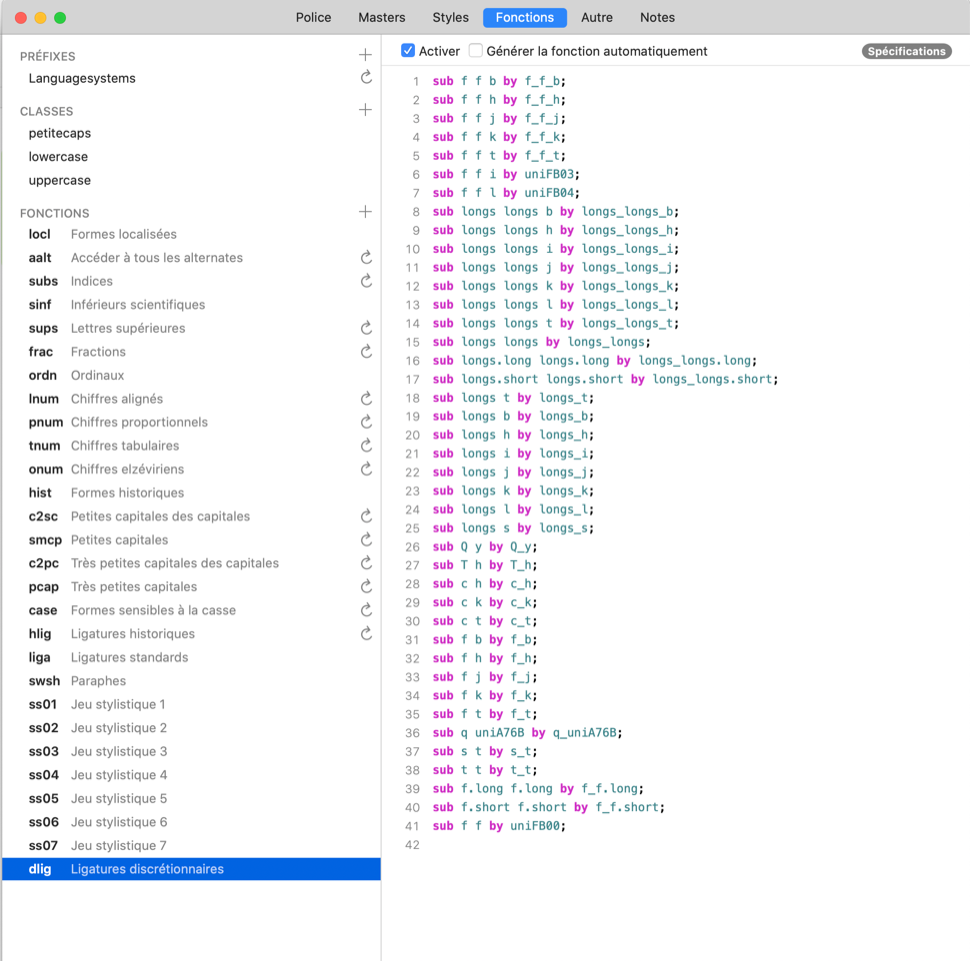
Message : Re: [typo] EB Garamond Variable. — Logiciel Glyphs (Mac OS) et ligatures
Subject:    Re: [typo] EB Garamond Variable. — Logiciel Glyphs (Mac OS) et ligatures
Je viens de télécharger le fichier .glyphs depuis le repo Github et ne vois aucun problème sur la fonte, qui est plutôt très bien développée. Pas de bugs sur le dessin des ligatures, des fonctions bien hiérarchisées, et toutes les espaces possibles.
Pourquoi avez-vous besoin de la fonte variable? Si c’est pour les ligatures, les OTF statiques suffisent amplement.
Pour activer ou pas les ligatures, l’EB Garamond dispose de différentes features OpenType pour activer ou non
— fi, fl, ffi, fil : LIGA (ligatures)
— ligatures s long : HLIG (ligatures historiques)
— fb, tt, ss, Qy… : DLIG (ligatures discrétionnaires)
Et sous HIST on peut activer les « formes historiques » comme le s long.
Le non-joiner est bien dans la fonte (U+200C), ainsi que toutes les espaces.
Plutôt que l’intégrer entre les glyphes, je vous recommande de n’activer que les features nécessaires. Ceci dit, la technique du non-joiner peut être utile pour faire des exceptions locales.
Dans l’urgence, si Octavio Pardo ne donne pas signe de vie ou que je ne
réussis pas à trouver un utilisateur de Glyphs disposé à me venir en
aide, j’ai trouvé un contournement qui suffira à régler le seul problème
majeur concernant l’usage des ligatures pour le client que j’évoquais :
introduire une espace de chasse nulle (WORD JOINER) entre certains
caractères pour bloquer les ligatures italiques « a/e/i/u-s »
indésirables au milieu d’un mot, empêchant de surcroît en italique les
ligatures attendues « st ») — un coup de chercher-remplacer avec
_expression_ rationnelle dans la copie, et le tour sera joué.
Évidemment, ça ne règle en rien les problèmes de substitutions de
glyphes, qui à l’examen du source se révèlent innombrables.
Georg Duffner, de son côté, m’a dit qu’il ne s’était pas occupé de la
version variable et qu’il ne disposait pas non plus des outils pour ce
faire. Je vais contacter Google Fonts (à l’origine du projet EB Garamond
Variable) dans l’espoir qu’ils trouveront quelqu’un pour sauver cette
police — il suffirait de reproduire le comportement de la police
d’origine, décrit dans la documentation de Duffner.  En l’absence de
réponse positive, peut-être contacter The League of Moveable Type,
quitte à proposer le lancement d’une campagne de financement participatif
pour « motiver les troupes » et accélérer les choses.
je ne
dispose malheureusement pas du logiciel utilisé par Octavio Pardo, à
savoir Glyphs pour Mac OS, pour générer de nouvelles fontes à partir
des deux fichiers (romain et italique).